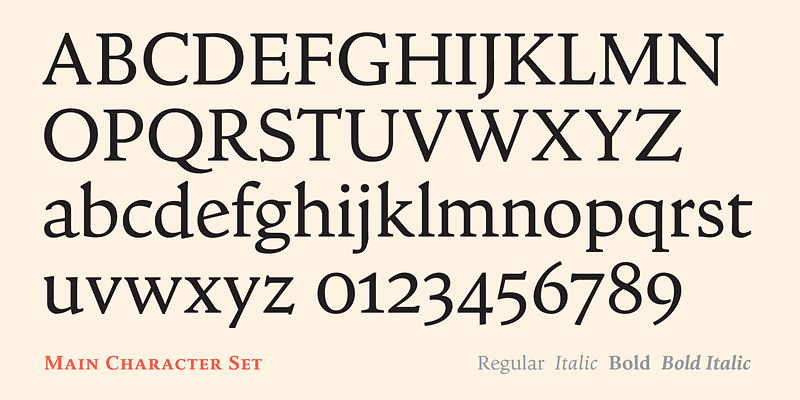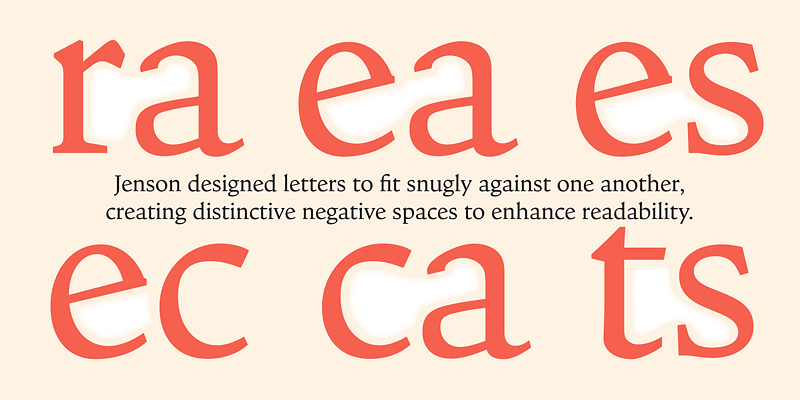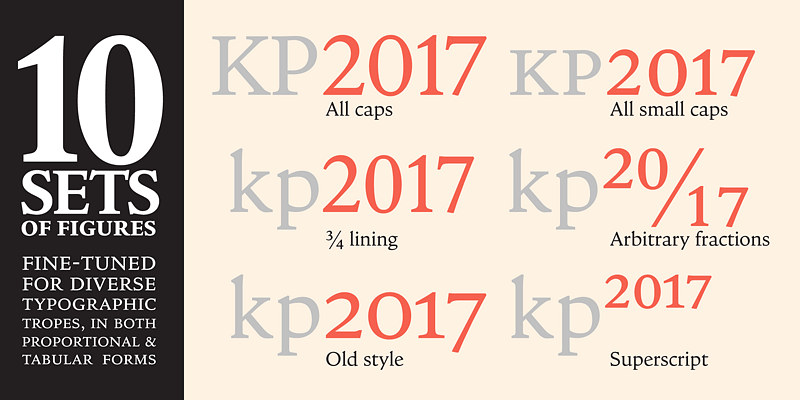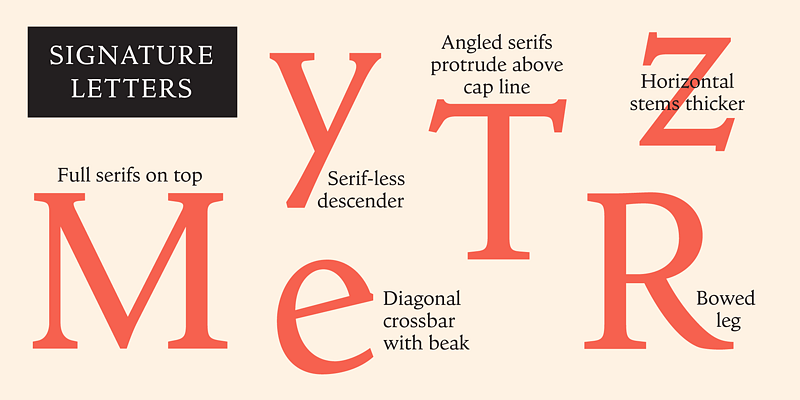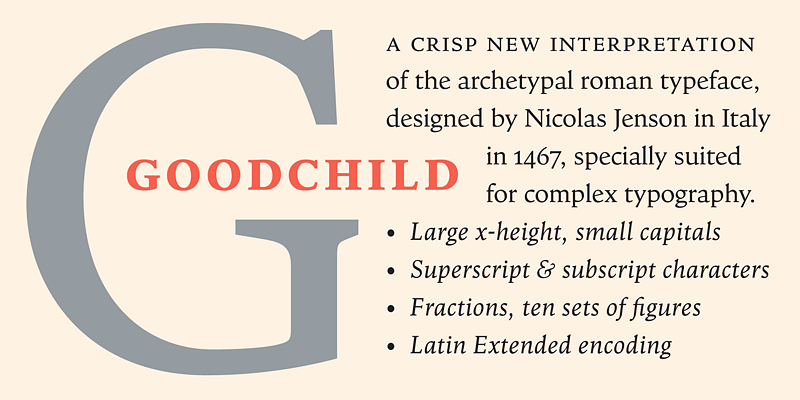
Goodchild ist eine pragmatische Jenson-Wiederbelebung, die für komplexe akademische Aufgaben gerüstet ist.
Das Gesicht hat eine große x-Höhe, denn es macht wenig Sinn, den Bestand an
von schlaksigen „Buch“-Jensons zu erweitern. Trotz dieser Abweichung vom Archetyp, bleibt Goodchild in anderer
Trotz dieser Abweichung vom Archetyp bleibt Goodchild in anderer Hinsicht den ursprünglichen Buchstabenformen treu, was die enge Schrift, die Modulation des Strichkontrasts und die Manipulation der x-Höhe und der Serifengröße betrifft. Die winzigen Titel und rautenförmigen Punkte von Jenson wurden jedoch aufgegeben.
Das Finish ist nicht so antikisiert, wie man es oft bei Renaissance-Revivals findet. Hier sorgen saubere, entschiedene Details für ein prägefrisches, zeitgenössisches Aussehen, das einen eleganten Eindruck vermittelt, wenn man die Schrift in Displaygröße verwenden möchte.
Diese Designs von Nick Shinn sind fest in der europäischen und nordamerikanischen typografischen Tradition verwurzelt, die sich ständig weiterentwickelt. Eine zuverlässige Textschrift mit allen Details professioneller Typografie und eine intelligente Display-Schrift mit Liebe zum makellosen Detail.